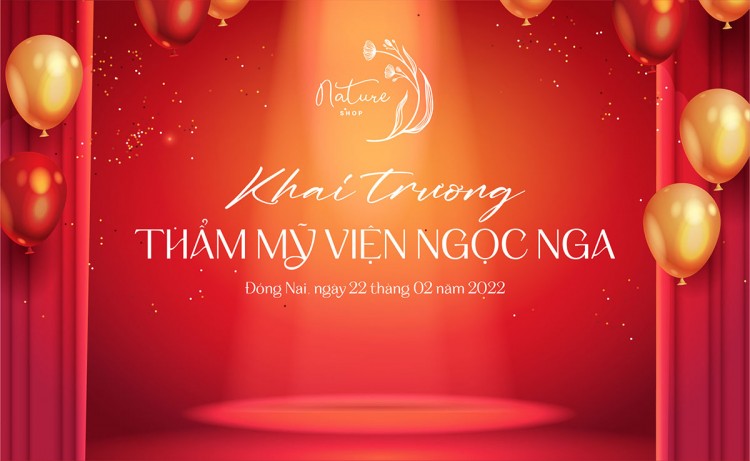
Combo font thiết kế khai trương 1 + Kèm file thiết kế Ai
Tầm quan trọng của bộ Combo font thiết kế khai trương 1 + Kèm file thiết kế Ai
Ngày khai trương là cột mốc đặc biệt quan trọng đối với bất kỳ cửa hàng hay doanh nghiệp nào tại Việt Nam. Để tạo ấn tượng mạnh mẽ ngay từ cái nhìn đầu tiên, việc lựa chọn Font Miễn Phí phù hợp đóng vai trò quyết định đến thẩm mỹ của bộ nhận diện thương hiệu. Bộ Combo font thiết kế khai trương 1 + Kèm file thiết kế Ai được tuyển chọn kỹ lưỡng nhằm mang lại sự sang trọng, tinh tế và không kém phần năng động cho các ấn phẩm truyền thông. Việc sở hữu một bộ phông chữ chuyên dụng không chỉ giúp tiết kiệm thời gian mà còn đảm bảo tính đồng nhất cho toàn bộ thiết kế từ bảng hiệu, băng rôn đến thiệp mời khách hàng.
Đặc điểm nổi bật của các font chữ trong bộ sưu tập
Các font chữ trong bộ combo này chủ yếu là những định dạng font việt hóa, giúp người dùng tránh được các lỗi hiển thị dấu tiếng Việt phổ biến. Đặc điểm của chúng là nét chữ rõ ràng, có độ tương phản cao, rất thích hợp cho các tiêu đề lớn cần sự thu hút. Ngoài ra, sự kết hợp giữa các nét dày mạnh mẽ và nét thanh mảnh hiện đại giúp bố cục thiết kế trở nên hài hòa hơn. Đây là công cụ đắc lực cho các bạn học sinh, sinh viên ngành thiết kế hoặc các chủ shop tự tay thực hiện maket quảng cáo cho ngày trọng đại của mình.
Hướng dẫn sử dụng Combo font thiết kế khai trương 1 + Kèm file thiết kế Ai hiệu quả
Để tận dụng tối đa sức mạnh của Combo font thiết kế khai trương 1 + Kèm file thiết kế Ai, người dùng cần có những kiến thức cơ bản về cách phối màu và sắp xếp bố cục. File thiết kế đi kèm dưới định dạng Adobe Illustrator (Ai) cho phép bạn chỉnh sửa linh hoạt từng chi tiết nhỏ nhất. Bạn có thể dễ dàng thay đổi kích thước mà không lo vỡ hình, đồng thời áp dụng các hiệu ứng gradient hoặc shadow để làm nổi bật tên thương hiệu. Việc tích hợp sẵn file gốc giúp quy trình làm việc trở nên chuyên nghiệp và nhanh chóng hơn bao giờ hết.
Lợi ích khi sở hữu file thiết kế Ai đi kèm
File Ai là định dạng vector chuẩn mực trong ngành in ấn. Khi sử dụng file này cùng với bộ font chữ chuyên dụng, bạn sẽ đảm bảo được chất lượng đầu ra tốt nhất cho các bản in khổ lớn như backdrop sân khấu hay banner treo ngoài trời. Điều này đặc biệt hữu ích khi bạn cần thay đổi thông tin ngày tháng hoặc địa chỉ mà vẫn giữ nguyên được phong cách thiết kế ban đầu. Sự tiện lợi này giúp các nhà thiết kế không chuyên cũng có thể tạo ra sản phẩm đạt chất lượng cao như các agency chuyên nghiệp.
Kết luận về bộ Combo font thiết kế khai trương 1 + Kèm file thiết kế Ai